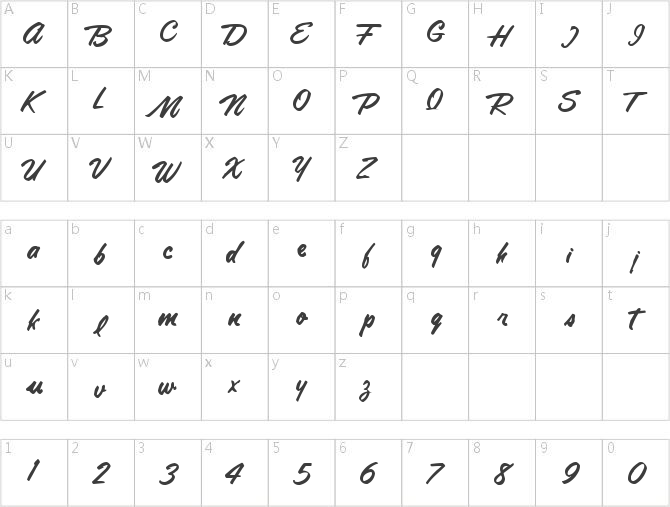
Tamte Semi-Script 詳情頁(yè)
Tamte Semi-Script字體字庫(kù)是一款讓人賞心悅目、百看不厭的英文字體,適合各類廣告和產(chǎn)品包裝設(shè)計(jì)應(yīng)用,字體大小0.06MB,格式為ttf字體,上傳用戶是23KUN,作者/版權(quán)方為未知